Thiết kế không chỉ là câu chuyện của màu sắc hay bố cục, mà còn là cách bạn truyền tải cảm xúc. Trong thế giới nghệ thuật thị giác, font chữ viết tay (handwritten fonts) luôn sở hữu một sức hút mãnh liệt. Chúng mang lại sự chân thật, tính cá nhân hóa cao và thổi hồn vào những ấn phẩm vô tri, biến chúng trở nên mềm mại và gần gũi hơn bao giờ hết.
Tuy nhiên, rào cản lớn nhất của các Designer Việt Nam là tình trạng lỗi dấu font chữ. Việc tìm được một font nước ngoài ưng ý nhưng lại “vỡ trận” khi gõ tiếng Việt có thể làm đứt gãy hoàn toàn mạch sáng tạo.
Hiểu được nỗi đau đó, bài viết này sẽ cung cấp cho bạn một giải pháp toàn diện: Bộ sưu tập 15+ font chữ viết tay đã được Việt hóa hoàn chỉnh 100%. Không còn lỗi font, không còn những dấu ngã, dấu hỏi lạc lõng. Dưới đây là danh sách đã được phân loại chi tiết cùng link tải an toàn để bạn ngay lập tức áp dụng vào dự án của mình.
Khi nào thiết kế của bạn cần sử dụng Font chữ viết tay?
Không phải ấn phẩm nào cũng phù hợp với sự bay bổng. Một chuyên gia thiết kế giỏi là người biết đặt đúng font chữ vào đúng ngữ cảnh. Ứng dụng font viết tay sẽ phát huy tối đa sức mạnh thị giác trong các trường hợp sau:
- Thiết kế thiệp cưới, thiệp mời sự kiện: Những nét chữ uốn lượn mang lại cảm giác vô cùng lãng mạn, thanh lịch và sang trọng. Sử dụng đúng font chữ thiệp cưới sẽ giúp người nhận cảm thấy họ đang cầm trên tay một lời mời trân trọng và đầy thành ý.
- Thiết kế Logo thương hiệu cá nhân, thời trang, mỹ phẩm: Các ngành hàng đòi hỏi tính thẩm mỹ cao, đề cao cái đẹp và sự độc bản rất ưa chuộng phong cách này. Một font chữ thiết kế logo dạng viết tay tạo ra sự khác biệt, giúp định vị thương hiệu như một “chữ ký” độc quyền không thể sao chép.
- Thiết kế trích dẫn (Quote), typography, bìa sách: Chữ viết tay đại diện cho tiếng nói nội tâm. Khi thiết kế các câu nói truyền cảm hứng hay bìa sách văn học, dạng font này giúp chạm đến cảm xúc của độc giả một cách tự nhiên và sâu sắc nhất.
TOP 15 Font chữ viết tay Việt hóa đẹp nhất
Để giúp bạn dễ dàng lựa chọn đúng mục đích thiết kế, bộ font dưới đây đã được chọn lọc khắt khe và chia thành 4 phong cách đặc trưng nhất.
Nhóm 1: Phong cách thanh lịch, mềm mại
Nhóm font này sở hữu đường nét mỏng, độ tương phản nhẹ nhàng, vô cùng lý tưởng cho thiết kế thiệp cưới, banner spa, mỹ phẩm hoặc các thương hiệu dành cho phái đẹp.
Font SVN Betalisa: Mang đặc trưng của sự nữ tính với những đường nét thanh mảnh, uốn lượn tự nhiên. Cảm giác khi nhìn vào Betalisa giống như nét bút lướt nhẹ trên mặt giấy.
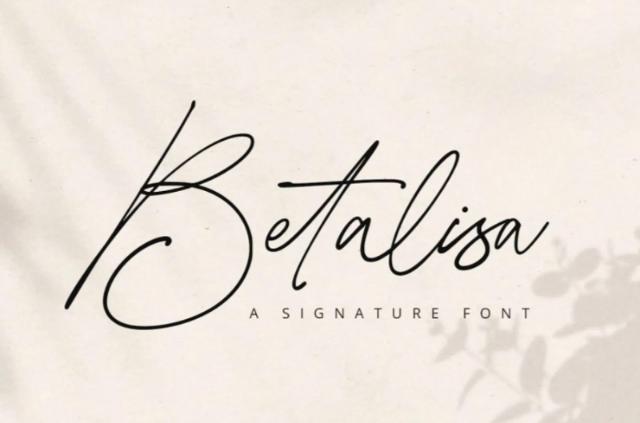
Font Fleur De Leah: Một sự kết hợp tinh tế của phong cách nghệ thuật Art Nouveau. Font chữ này bay bổng, hoa mỹ nhưng không hề tạo cảm giác nặng nề.
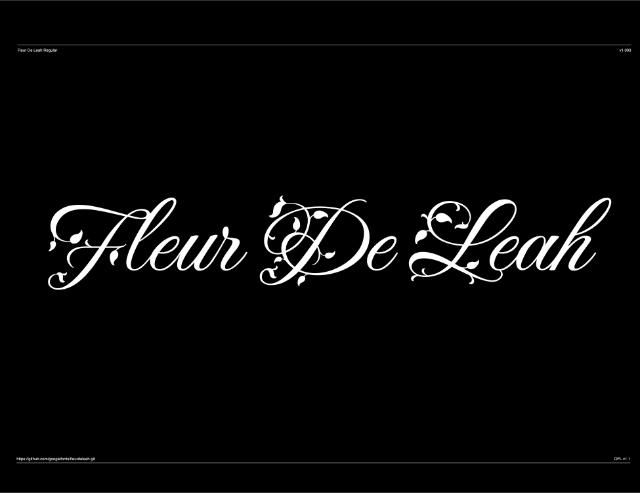
Font Loveya Script: Nếu bạn đang tìm kiếm cảm giác thư pháp hiện đại (calligraphy) thì đây là lựa chọn hoàn hảo. Các nét nối giữa những chữ cái vô cùng uyển chuyển, mang đậm chất thơ và sự lãng mạn.
Font TH Milyah: Điểm mạnh lớn nhất của TH Milyah là tính dễ đọc. Dù vô cùng mềm mại và nghệ thuật, cấu trúc chữ vẫn rất rõ ràng, an toàn cho các bài viết nghệ thuật hoặc thiệp chúc mừng cỡ nhỏ.
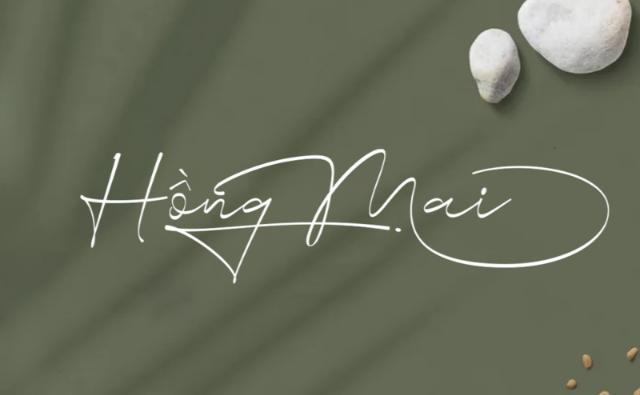
Font Alex Brush: Một biểu tượng của sự cổ điển và quyến rũ. Nét cọ của Alex Brush uyển chuyển, dày dặn hơn một chút, gây ấn tượng mạnh về thị giác ngay từ cái nhìn đầu tiên.
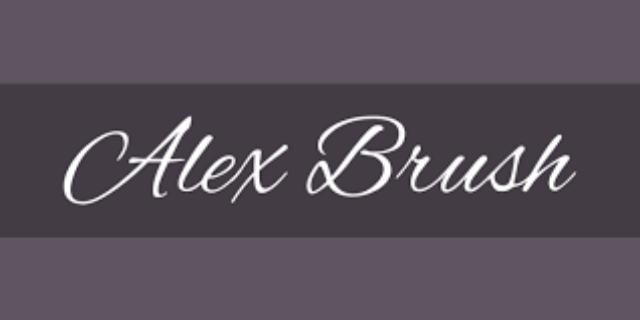
Nhóm 2: Phong cách cá tính, hiện đại & tự do
Dành cho những tâm hồn thích sự phá cách. Nhóm này sử dụng nét cọ xước (brush) hoặc bút marker, cực kỳ phù hợp cho thiết kế poster sự kiện, typography cho giới trẻ, hay các thương hiệu đồ uống, streetwear.
Font SVN Lemon Tuesday: Nổi loạn và ngẫu hứng. Nét viết tự do bằng cọ xước tạo ra một nguồn năng lượng bùng nổ, rất hợp cho những tiêu đề cần sự chú ý mạnh.
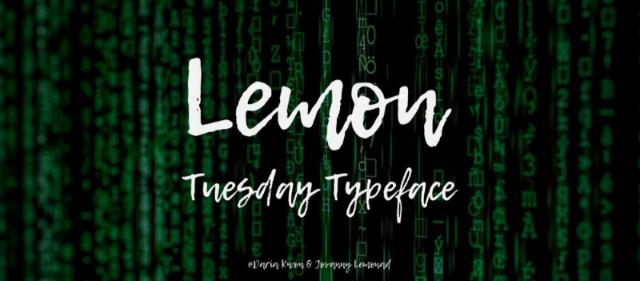
Font Selima: Sở hữu đường nét mạnh mẽ, dứt khoát. Dạng cọ vẽ của Selima sinh ra là để làm Heading nổi bật trên nền hình ảnh phong cảnh hoặc lookbook thời trang.
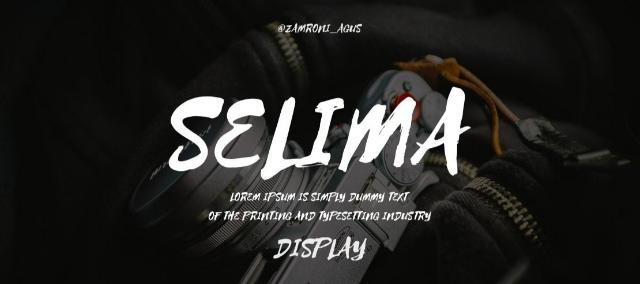
Font TH Modernline: Đây là sự giao thoa tuyệt vời giữa nét viết tay mềm mại và cấu trúc chữ hiện đại. Nó không quá hoang dại như Lemon Tuesday nhưng vẫn giữ được sự trẻ trung, năng động.
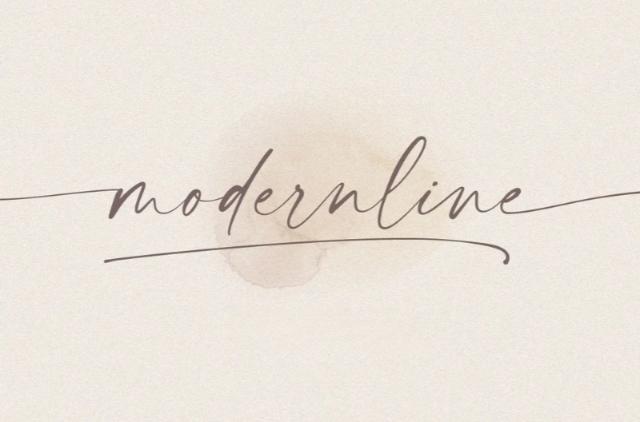
Font Patrick Hand: Thay vì dùng cọ, Patrick Hand mô phỏng nét chữ viết tay thật bằng bút mực. Sự mộc mạc, có phần “vụng về” một cách cố ý của nó mang lại sự gần gũi, chân thật đến bất ngờ.
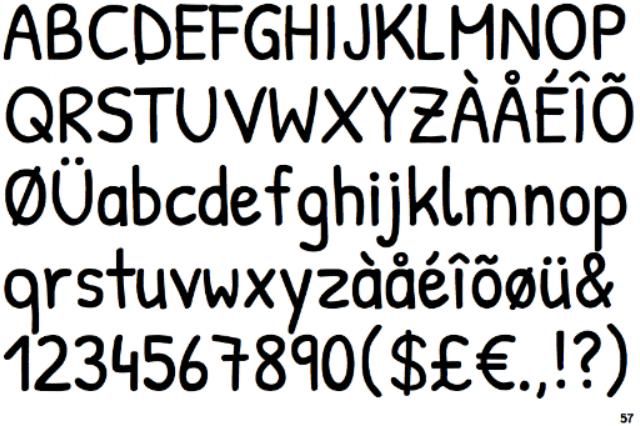
Nhóm 3: Phong cách Sang trọng & Chữ ký (Signature)
Muốn thiết kế trông “đắt tiền” và đẳng cấp? Nhóm font chữ ký chính là vũ khí bí mật của bạn.
Font SVN Housttely Signature: Thanh thoát và vô cùng sang trọng. Housttely mang dáng dấp của một chữ ký đẳng cấp từ một vị CEO hoặc một nhà thiết kế danh tiếng.
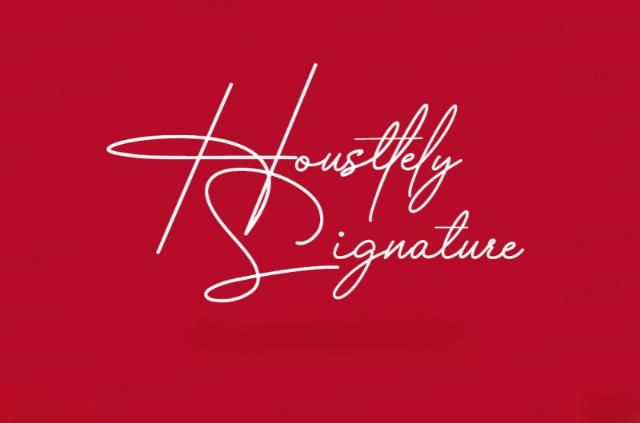
Font Autography: Mang đậm DNA cá nhân. Font chữ này hoàn hảo để làm tagline phía dưới logo hoặc dùng làm watermark (đóng dấu bản quyền) trên các tác phẩm nhiếp ảnh.
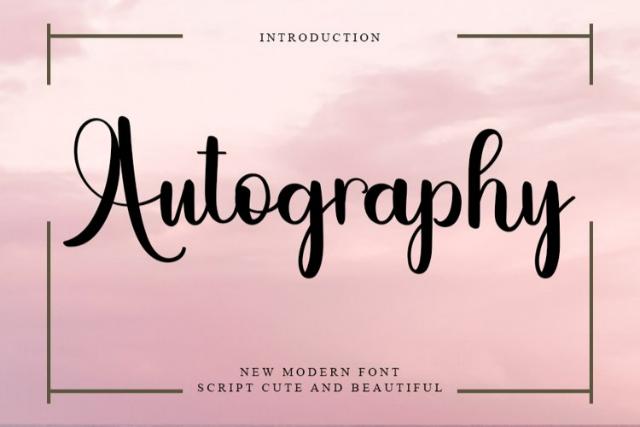
Font MTD Great Vibes: Uốn lượn sắc sảo, đường nét được chăm chút tỉ mỉ đến từng pixel. Great Vibes mang lại một cảm giác cực kỳ cao cấp, thường thấy ở các thương hiệu trang sức.
Một font chữ viết tay đẹp không chỉ làm tăng giá trị thẩm mỹ của tác phẩm mà còn là “vũ khí” giúp bạn kết nối cảm xúc với người xem. Hy vọng với bộ sưu tập 15+ font chữ viết tay Việt hóa đa dạng phong cách trên đây, bạn đã tìm được “mảnh ghép” hoàn hảo để nâng tầm cho dự án thiết kế tiếp theo của mình.